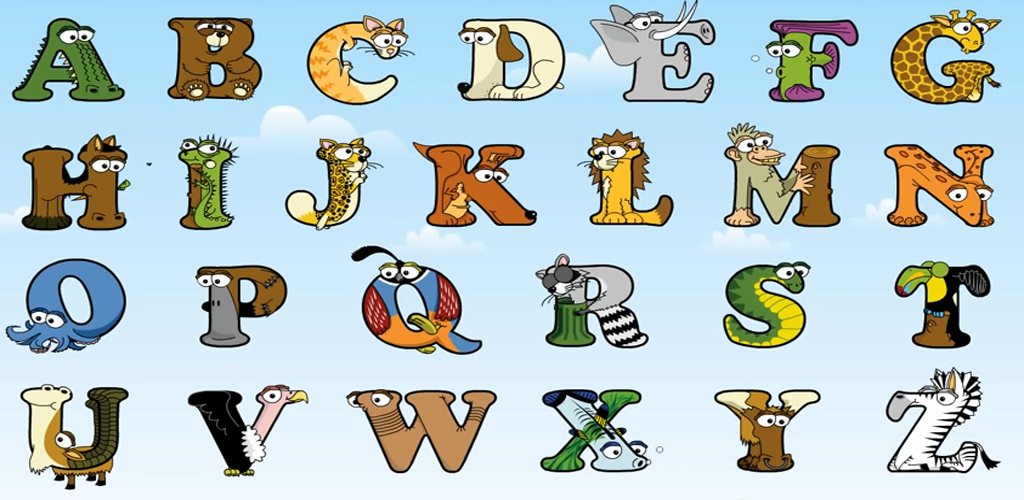
Шрифт Animal Comedians , Дингбаты — Животные шрифты
При создании комиксов большое внимание уделяется звуковым эффектам — словам, основная задача которых заключается в воспроизведении звуков на картинках.
Благодаря им комиксы становятся более интересными и удобочитаемыми, персонажи — более живыми и понятными. В зависимости от типа звук можно записать разными размерами, формами, начертаниями. Можно воспользоваться набором специальных шрифтов, либо придумывать шрифты самим и рисовать от руки, тем более, что четких правил их рисования не установлено. Для быстроты и удобства обычно используют готовые экземпляры, которые несложно найти в интернете.
Ниже приведена подборка наиболее часто встречающихся шрифтов для воссоздания звуков в комиксах.
Рассмотрим другие звуки, которые художники часто используют для того, чтобы оживить ситуацию или персонажа.
Молния, вспышки
Звуки ненастья, плохой погоды ассоциируются с молнией, вспышками, иногда эти шрифты используются для изображения салютов. Занимают большую часть кадра, по задумке автора могут быть перевернуты или искривлены.
Драка
Звуки, которые слышим во время борьбы. Например, Супергерой дерется со злодеем, спасая планету, в другой истории герои выясняют отношения с помощью кулаков на ринге, улице или в другом месте и т.
д. Звуки выписываются крупными шрифтами над фигурами дерущихся, либо находятся на заднем плане.
Смех
Написание звуков смеха зависит от типа, громкости (от неуемного, гомерического хохота до тихого «хи-хи») и продолжительности («ха-ха-ха» или «ха»). Кроме того, смех зависит от персонажа — выражения его лица, положения тела( от хохота хватается за живот, хлопает себя по коленям). Может прописываться в отдельный «пузырь».
Плач
Звук, противоположный звукам смеха. Прописывается тонким шрифтом, выражается звуком «у-ху-ху», унынием, мрачной атмосферой, сгустившейся над головой героя.
Крик, призыв о помощи
Звук о помощи может исходить из раскрытого рта героя, может выражаться персонажами, находящимися за кадром. Степень отчаяния обуславливается ситуацией и идеей комикса. Может прописываться в отдельный «пузырь».
Знаки препинания
Используются, чтобы подчеркнуть значение и усилить эмоции. В отличие от текста выделяются жирным и крупным шрифтом.
С этой же целью используются восклицательные знаки.
Боль
Звуки, выражающие страдания могут повторяться в разных моментах и ситуациях.
Сон
Звуки, которые издают герои во время сна. Прописываются по-разному в зависимости от глубины и продолжительности сна. Для глубокого сна подходит храп (изображается большими буквами) и многочисленные «хр», для легкого, непродолжительного сна можно использовать просто «Хр-хр».
Чихание
Эти звуки используют, когда персонаж болеет или попал под дождь.
Обед за столом
Звуки, издаваемые некоторыми героями комиксов во время застолья. Тем более, что многие из них поглощают пищу довольно шумно.